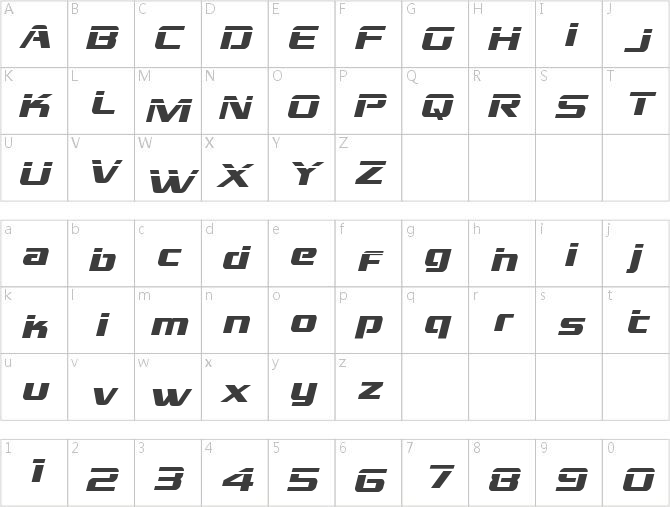
Grand National Laser Italic 詳情頁(yè)
Grand National Laser Italic字體字庫(kù)是一款讓人賞心悅目、百看不厭的英文字體,適合各類廣告和產(chǎn)品包裝設(shè)計(jì)應(yīng)用,字體大小0.03MB,格式為ttf字體,上傳用戶是dqq520,作者/版權(quán)方為未知